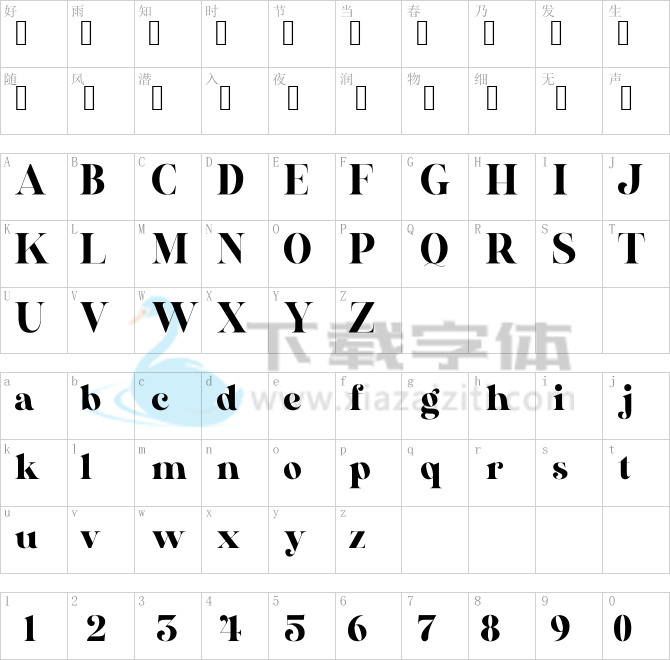
Al_Veshion_PersonalUseOnly.ttf字体下载,这款字体结构工整、笔画清晰,兼顾美观与易读性,适用于标题、正文、海报、包装、LOGO 等多种场景。字形优雅稳定,风格百搭耐看,适配日常排版与创意设计,让文字呈现更舒适、更具质感。Al_Veshion_PersonalUseOnly.ttf字体下载一笔一画,皆是细节,以均衡的比例、流畅的线条打造舒适视觉体验,字形端正大气,风格简约现代。无论是商业设计、品牌宣传还是日常排版,都能轻松驾驭,让文字更有格调与力量。Al_Veshion_PersonalUseOnly.ttf字体下载字体下载。